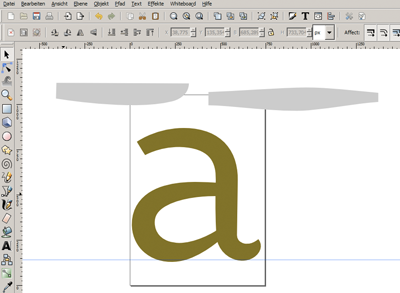
Inkscape nun mit Spiro-Support
Ich hatte das mal in einer Vorversion gesehen und war beeindruckt. Möchte man direkt mal was scriptiges entwerfen ... Gebt mir mehr Stunden pro Tag, bitte ...
Das Video: lustig, wie er es ganz zum Schluss noch verschlimmbessert :)
kann inkscape mitlerweile cmyk? ich werde den tag feiern an dem eine weiterentwickelte alternative zu illustrator da ist. und ja, ich trauere freehand immernoch nach...
ok ich formuliere es anders: sind diese cmyk angaben farbtreu oder handelt es sich um umgerechnete rgb werte? wie siehts mit volltonfarben aus?
Tatsächlich ... das ist ja der Hammer. Version 0.46 hat keine richtige cmyk Unterstützung. Ich habe es gerade ausprobiert. Einem Objekt eine cmyk-Farbe zuweisen, dann Objekt loslassen und wieder selektieren und die Farbwerte haben sich geändert!
Ist ja eigentlich eine Frechheit sowas zu machen ...
Andererseits kann man durchaus die besseren/anderen Zeichenwerkzeuge nutzen und die Zeichnungen dann in Illustrator weiterverarbeiten.
Ich hab auch schon Logos in Fontlab gezeichnet und dann Richtung Illustrator kopiert, weil ich da mit der Tastatur die Bezier-Handler schrittweise verschieben kann und ich so mehr Kontrolle habe was genau passiert.
Hab's gerade mal ausprobiert. (Mit dem letzten Windows-Snapshot vom 30. August)
Schon eine ganz andere »Denke« mit diesen Spiralen, da man ja die Form nicht mehr durch die Anfasser gezielt beeinflussen kann, sondern allein durch die Position und Anzahl der Punkte bestimmt. Da muss man es erstmal schaffen, eine gewünschte Form überhaupt hinzubekommen. Das Schreibschrift-D in dem Beispiel ist da clever gewählt, da es eine einzelne durchgängige Kontur ohne Geraden ist. Ein Grotesk-B geht mit Spiro nämlich gar nicht so toll.
Der eigentliche Clou ist ja aber auch die Funktion, ein variables Objekt auf den Pfad zu »spannen«. Und das geht sogar mit normalen Bézier-Pfaden – das Spiro braucht man da gar nicht:
Man kann sogar ein Ausgangsobjekt auf mehrere Segmente oder Buchstaben legen und damit Strichstärke und Kontrast global bestimmen. Leider ist dann die Schattenachse nicht konstant, wenn der Pfadanfang nicht an der gleichen Stelle beginnt.
Insgesamt aber sehr interessant für’s digitale Skizzieren! Zumal InkScape die gleiche Art der Vektorbearbeitung hat wie CorelDRAW. Illustrator ist ja für’s Typedesign ein Krampf.